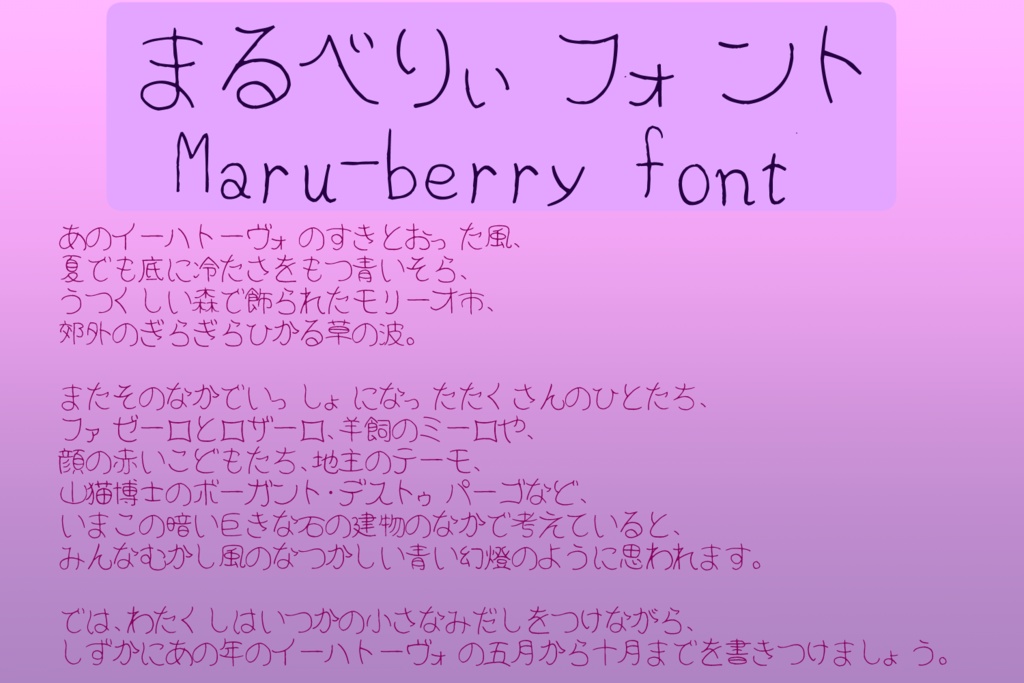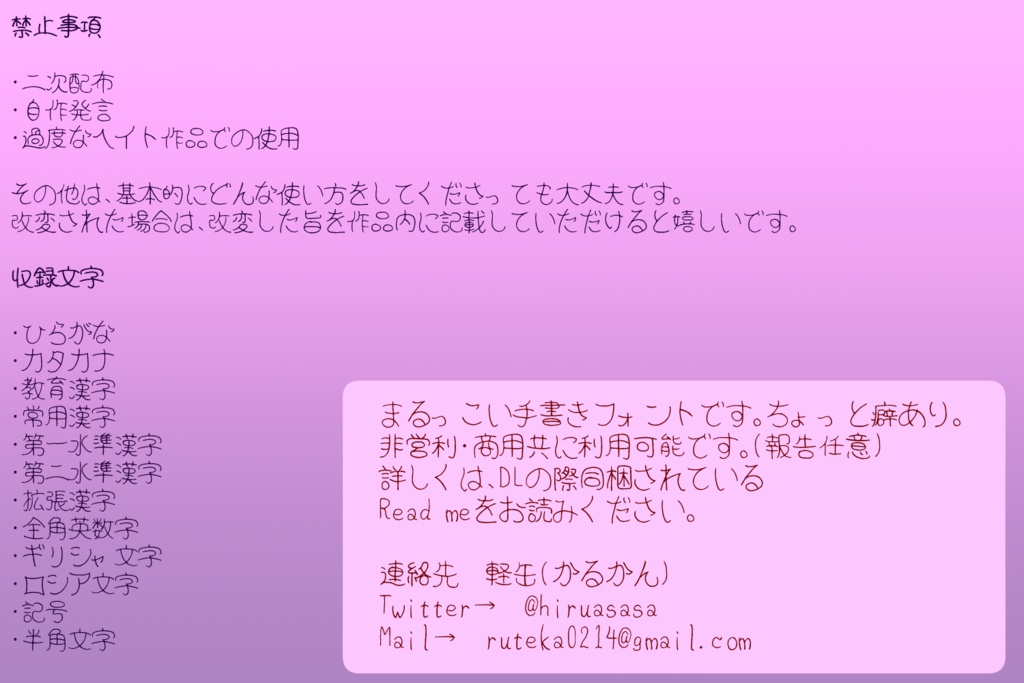
Maru berry手写字体字体信息
[记录字符]
- 平假名
- 片假名
- 教育汉字
- 常用汉字
- 第一水准汉字
- 第二水准汉字
- 扩张汉字
- 全角英数字
- 希腊字母
- 俄文字母
- 记号
- 半角文字
“Maru berry手写字体”是一款书写很新颖的字体,字体大方,适合各种设计作品使用!欢迎下载!